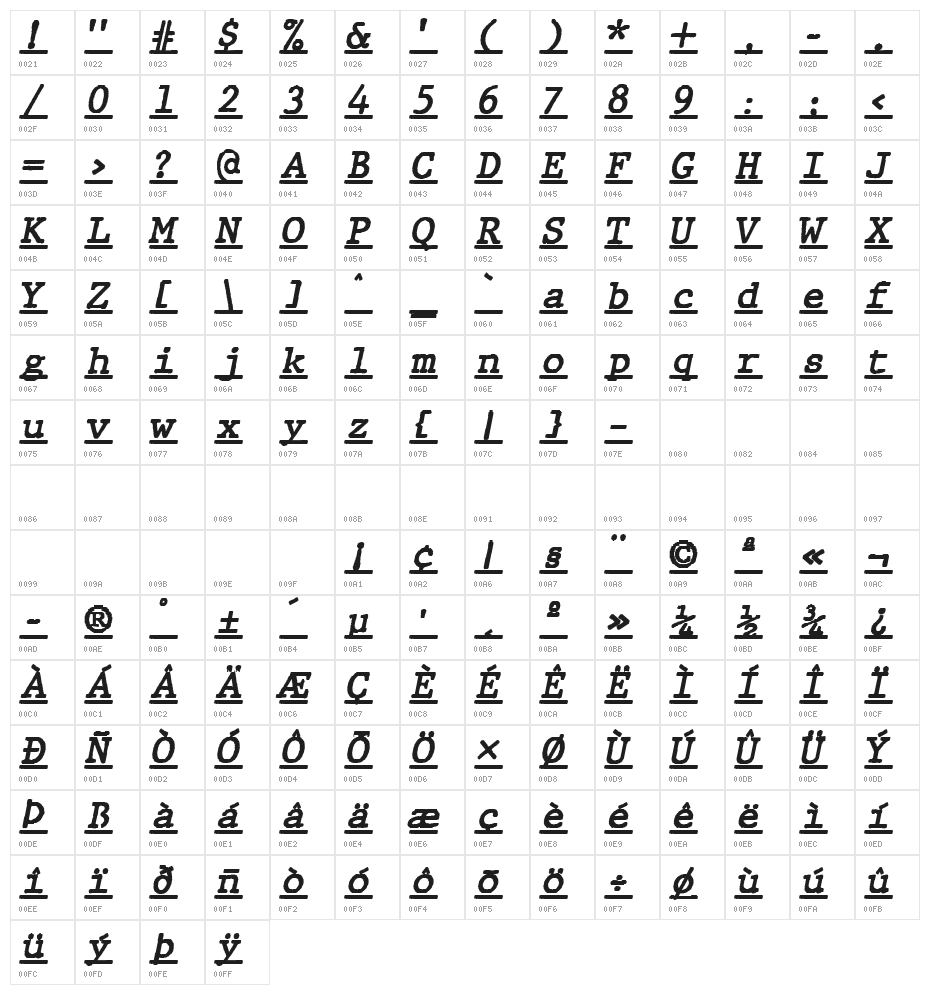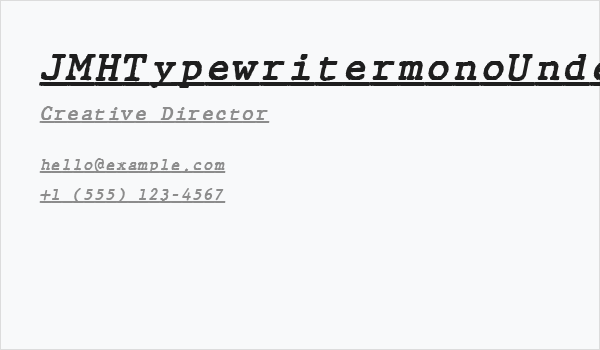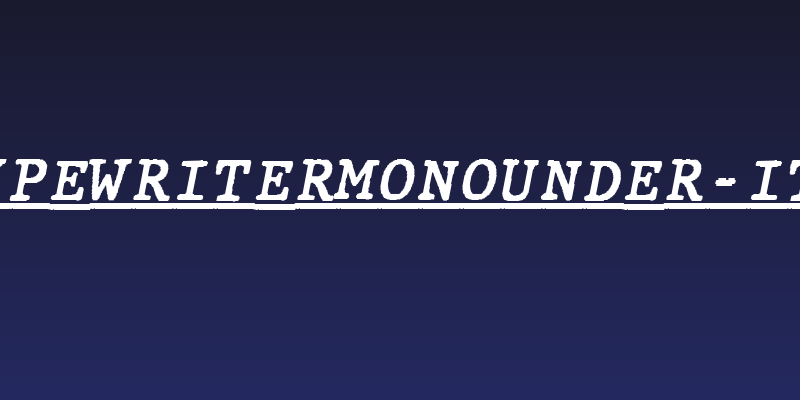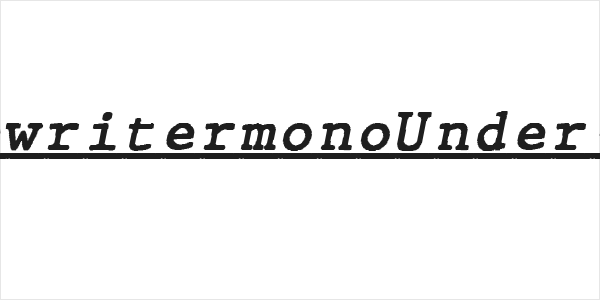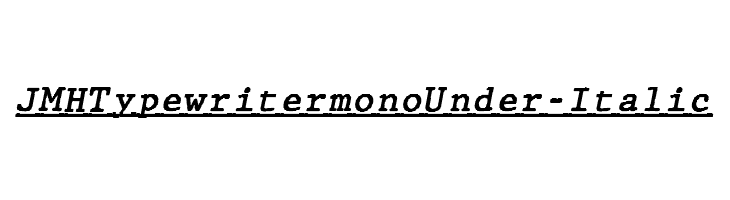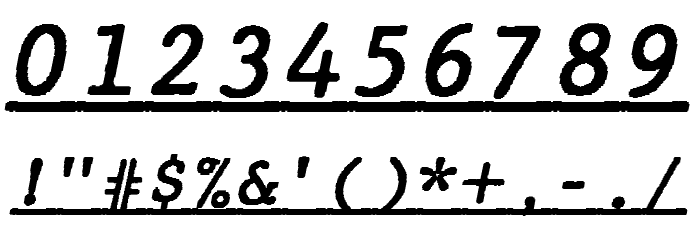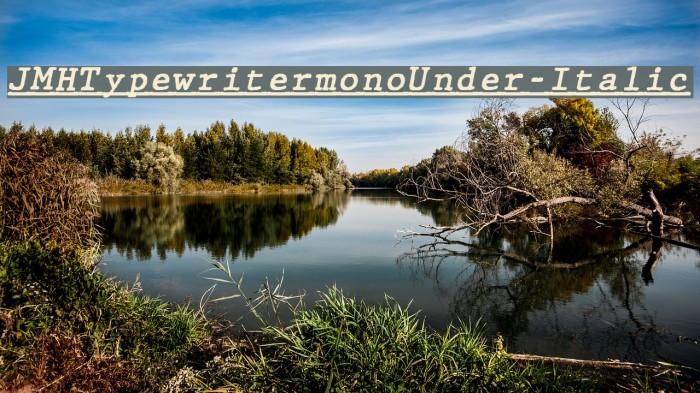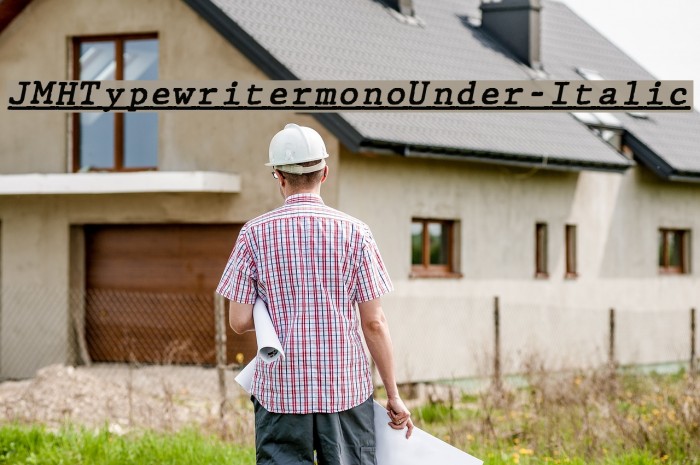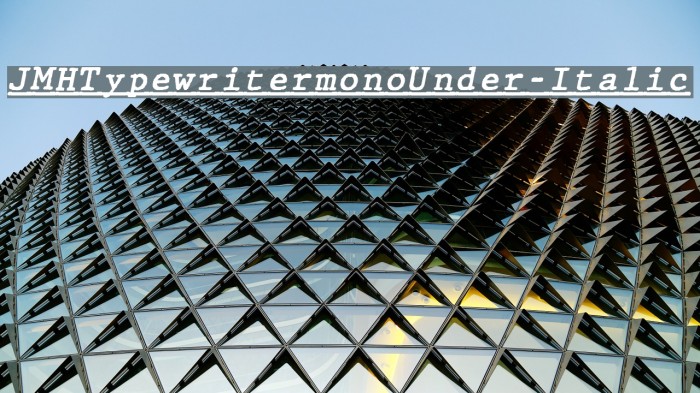
JMHTypewritermonoUnder-Italic Font
| Cas d'utilisation | Logos, Coding, Retro designs |
| Projets proposés | Ideal for retro-themed designs, coding projects, typewriter art, and vintage branding. |